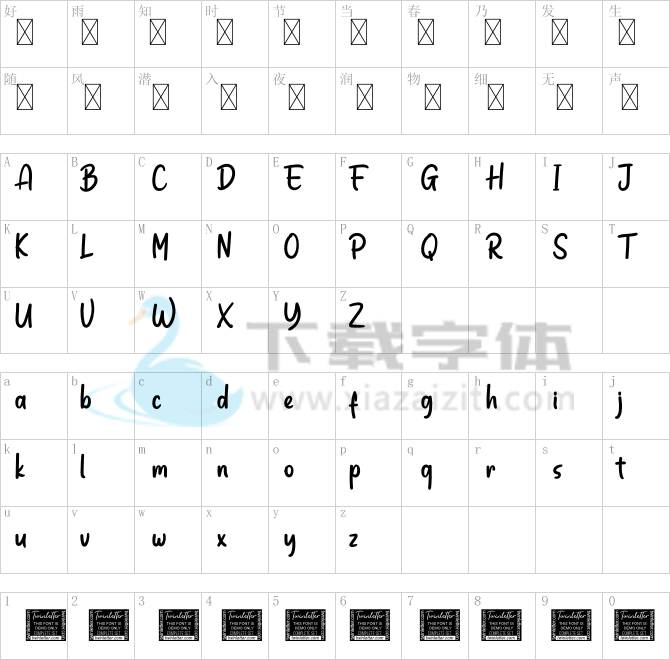
Asegunt Personal.otf字体下载,这款字体结构工整、笔画清晰,兼顾美观与易读性,适用于标题、正文、海报、包装、LOGO 等多种场景。字形优雅稳定,风格百搭耐看,适配日常排版与创意设计,让文字呈现更舒适、更具质感。Asegunt Personal.otf字体下载一笔一画,皆是细节,以均衡的比例、流畅的线条打造舒适视觉体验,字形端正大气,风格简约现代。无论是商业设计、品牌宣传还是日常排版,都能轻松驾驭,让文字更有格调与力量。Asegunt Personal.otf字体下载字体下载。